릭스폰트, 폰트 구독 플랫폼으로 도약… 국내외 파트너사 입점
국내 기업 4개사 및 해외 기업 1개사 협력
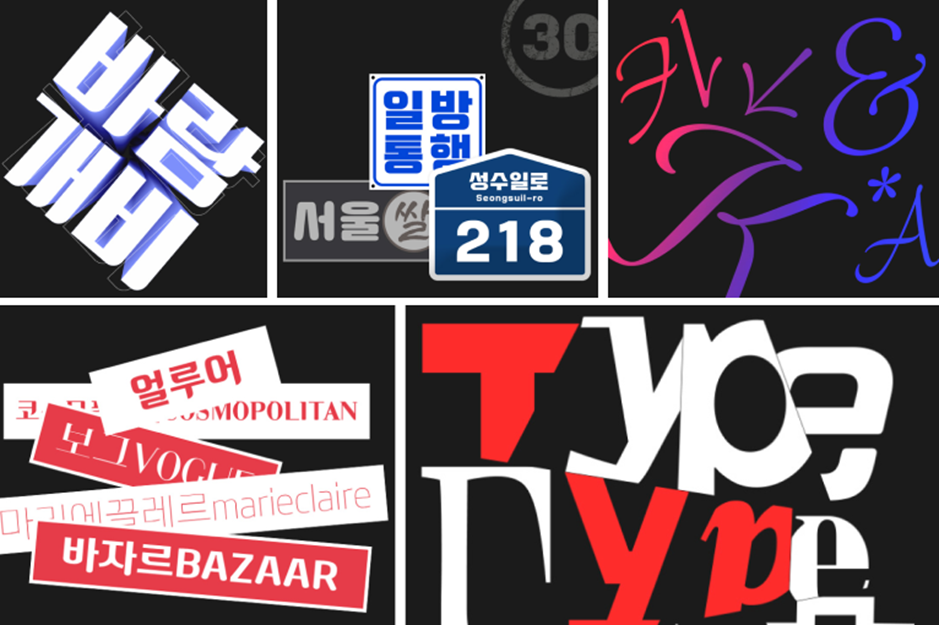
폰트릭스의 폰트 구독 플랫폼 ‘릭스폰트’가 국내외 폰트 5개사와 입점 계약을 맺었다고 4일 밝혔다.
폰트릭스는 기본에 입각한 폰트의 완성도와 안정감은 유지하면서 새롭고 다양한 가치를 가진 파트너사와의 제휴를 통해 이용자에게 구독의 다양성과 만족감을 높여 폰트 구독 플랫폼으로 도약한다는 계획이다.
입점 5개 파트너사는 국내 기업 4개사(다온커뮤니케이션, 닥터폰트, 티랩, 타이포디자인연구소)와 해외 기업 1개사(TYPETYPE)다. 각 브랜드별 주요 특징은 △한글의 감성을 시각적으로 풀어낸 ‘다온폰트’ △주목성과 가독성이 높은 헤드라인 서체에 주력한 ‘닥터폰트’ △실험 정신으로 새로운 디자인을 선보이는 ‘티랩’ △한글의 조형미를 표현한 ‘타이포디자인’, △국내 최초 입점한 라틴폰트 ‘TypeType’ 등이다.
김원준 폰트릭스 대표는 “릭스폰트 플랫폼은 이용자의 경험 스펙트럼을 확장하고 다양한 상호 거래 환경 속에서 네트워크 효과를 창출하여 성장을 가속화해 나갈 계획”이라고 밝혔다.
한편, 폰트릭스는 2005년 설립된 타입 디자인 전문 회사로 740여 종의 폰트를 보유했다. 삼성전자 ‘Samsung One’, 네이버 ‘나눔서체 시리즈’, 현대카드 ‘모던’, 카카오, MBC, CJ, 티몬, 넥슨 등의 유명 서체를 개발했으며, 디지털 콘텐츠 산업의 패러다임 변화에 대응해 폰트 구독 플랫폼 ‘릭스폰트’을 운영하고 있다.